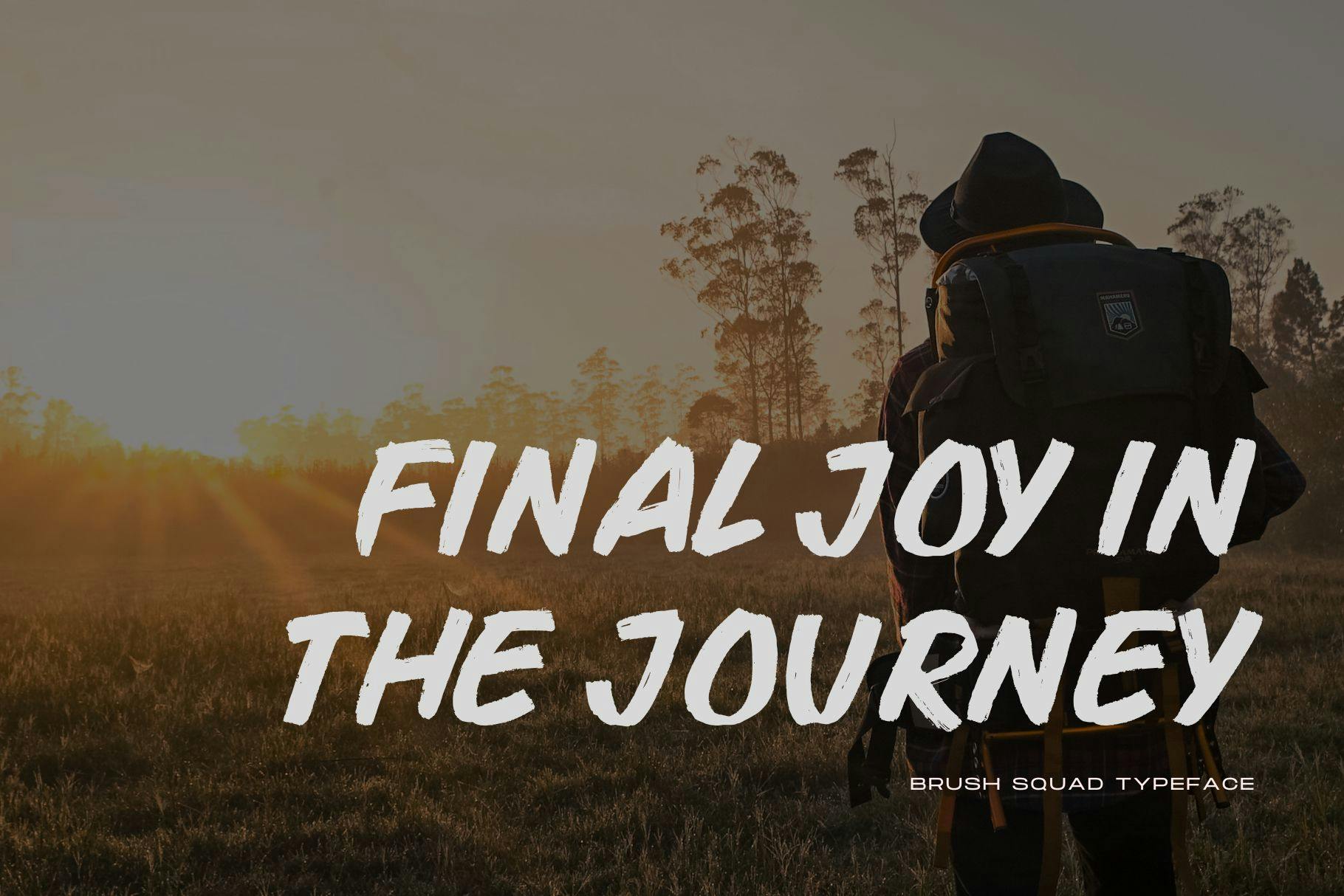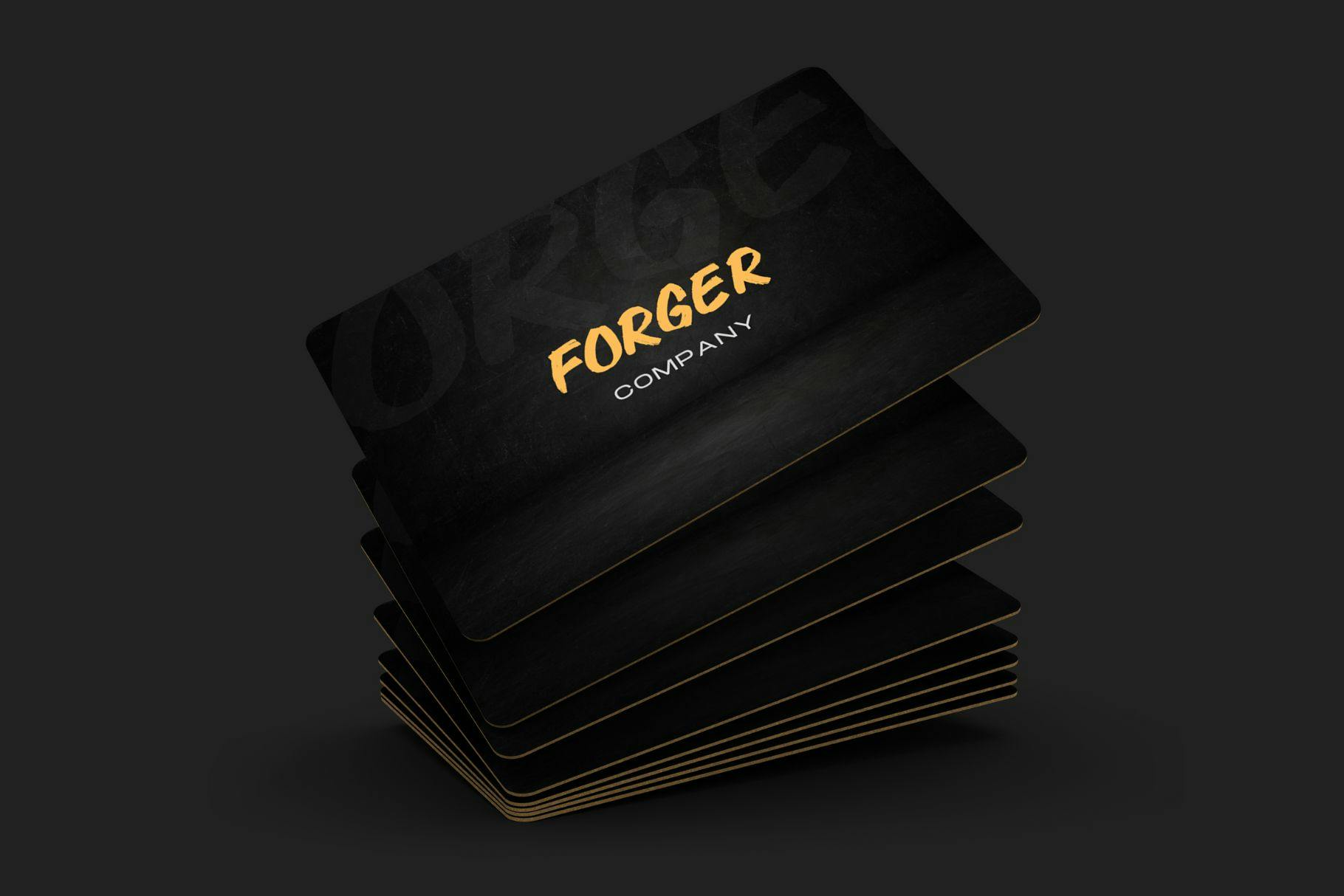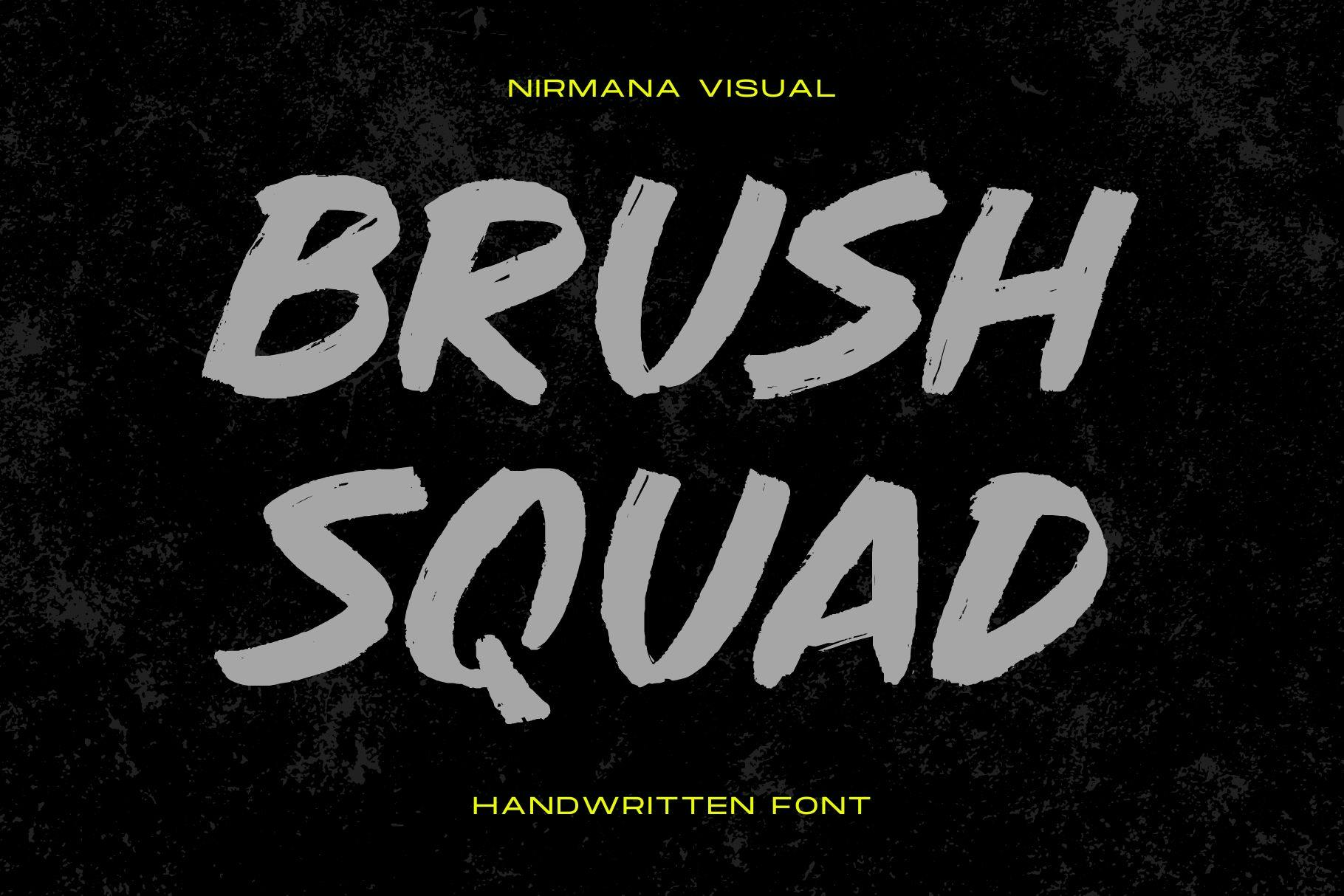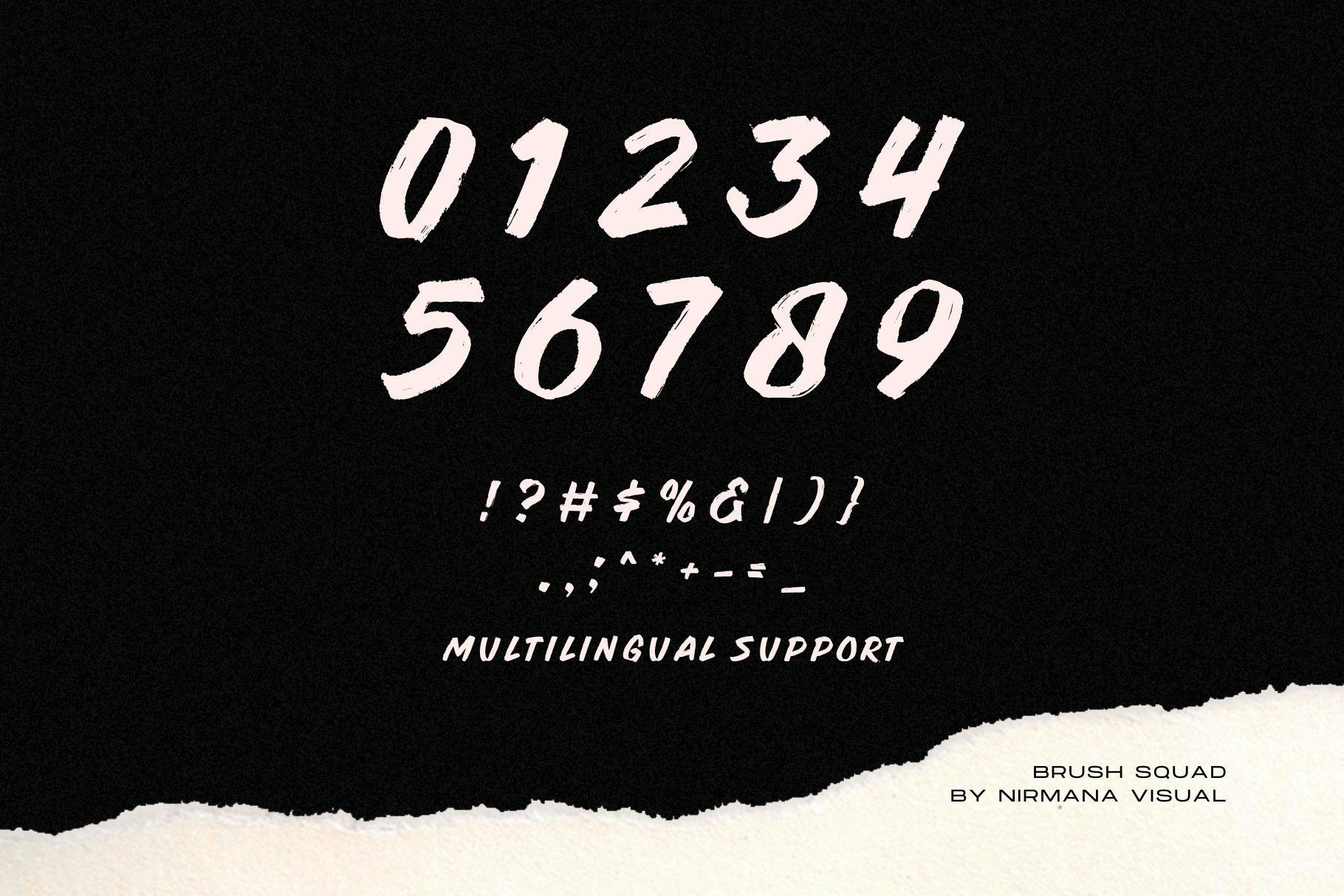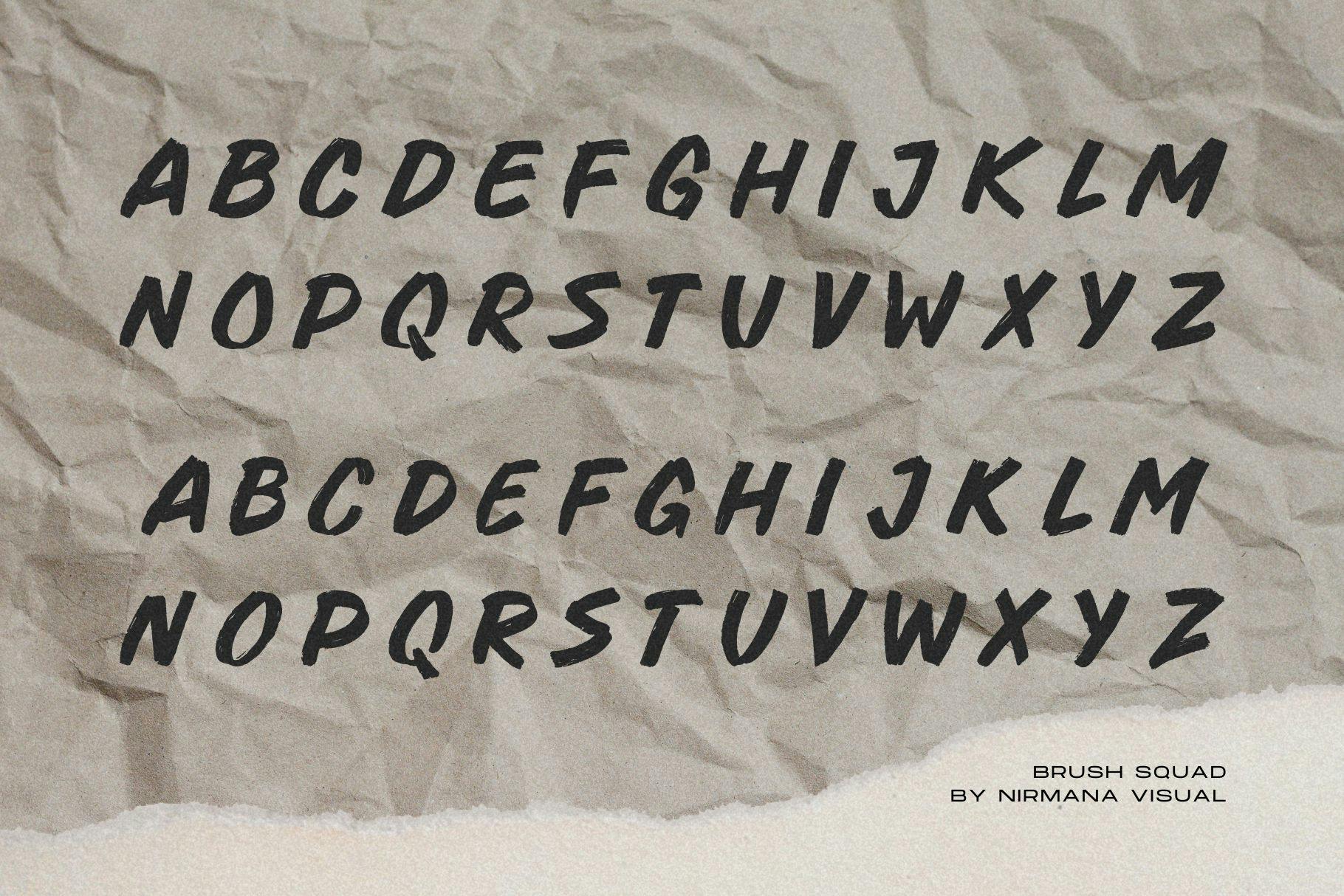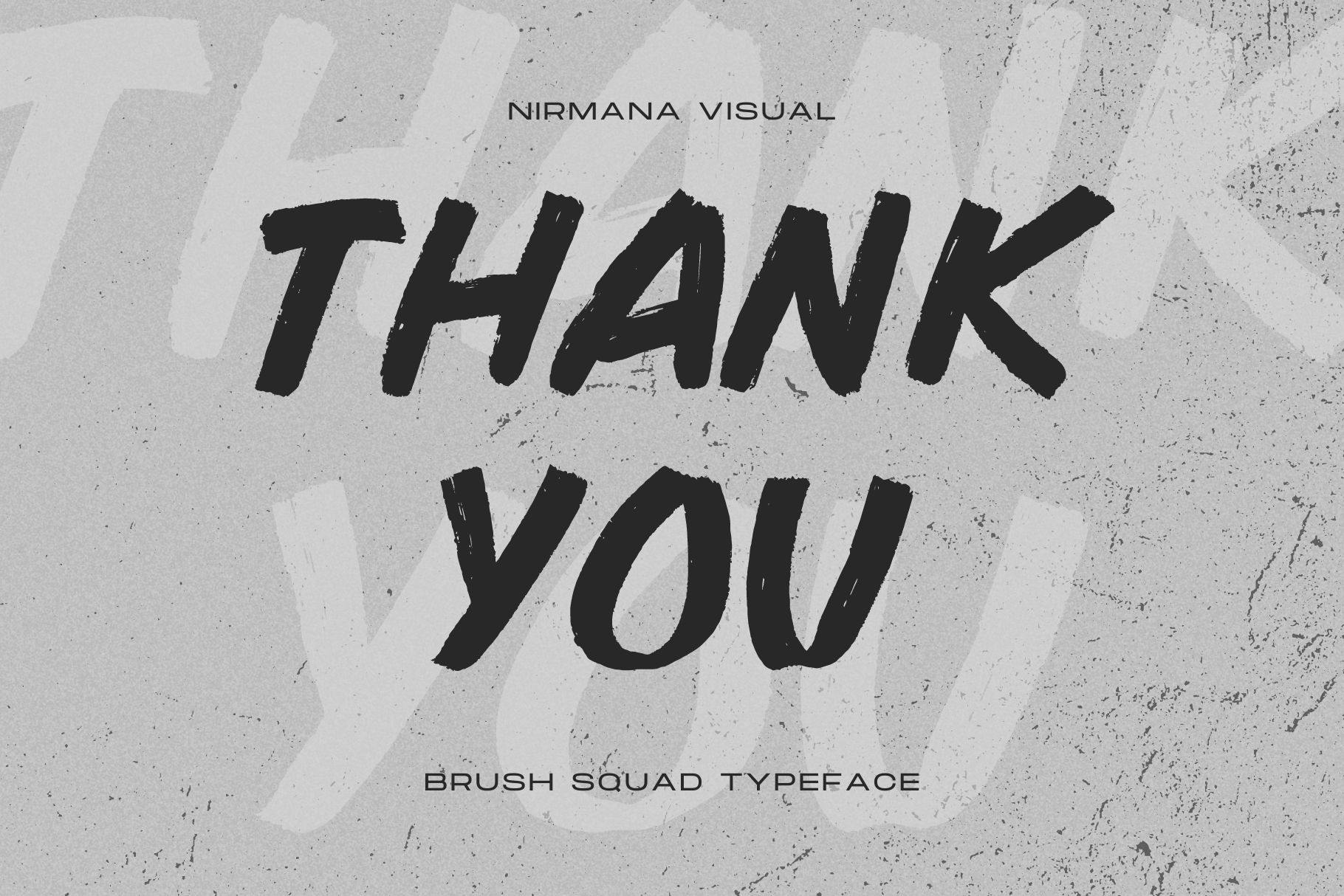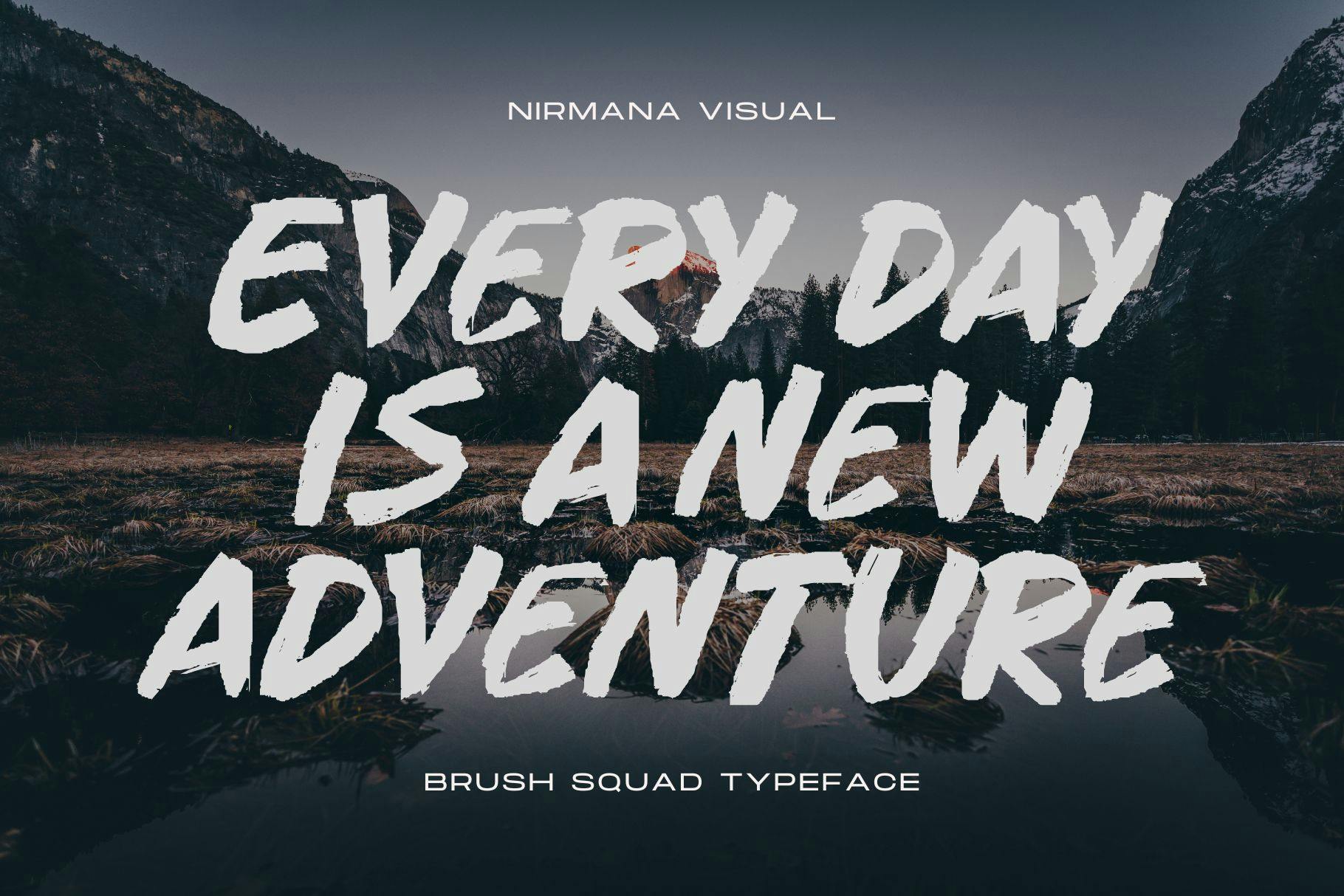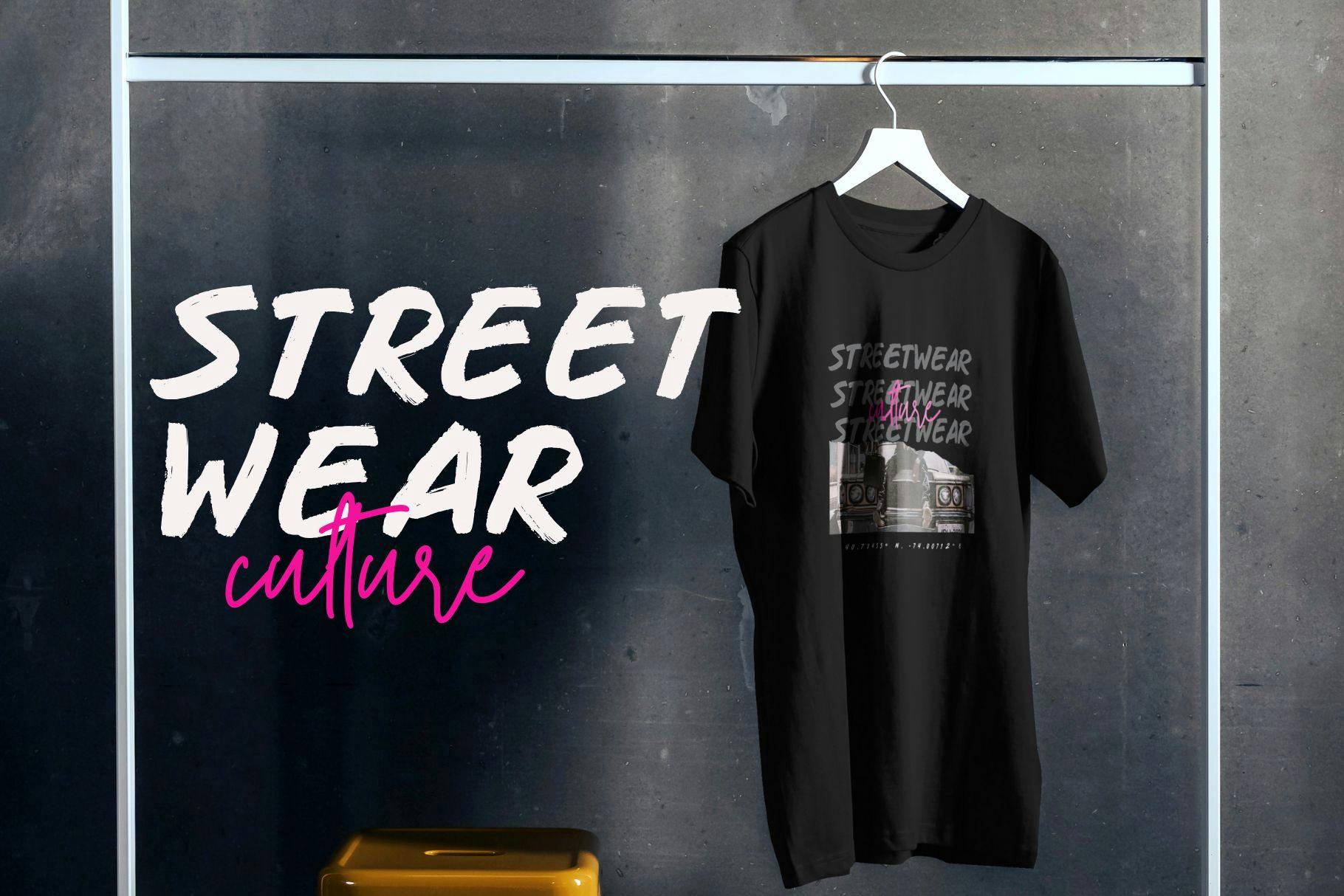
فونت Brush Squad یک نوع خط دستنویس با طراحی خشک است که شامل مجموعهای کامل از حروف بزرگ و کوچک، اعداد و نشانههای نگارشی و همچنین نمادهای چند زبانه میباشد.
این فونت بسیار مناسب برای طراحی عنوانها، لوگوها، تایپوگرافی، لباسها، مجلات، بروشورها، بستهبندی و بسیاری دیگر از نیازهای طراحی شماست و به طرحهای شما ظاهری مدرن و حرفهای میبخشد.